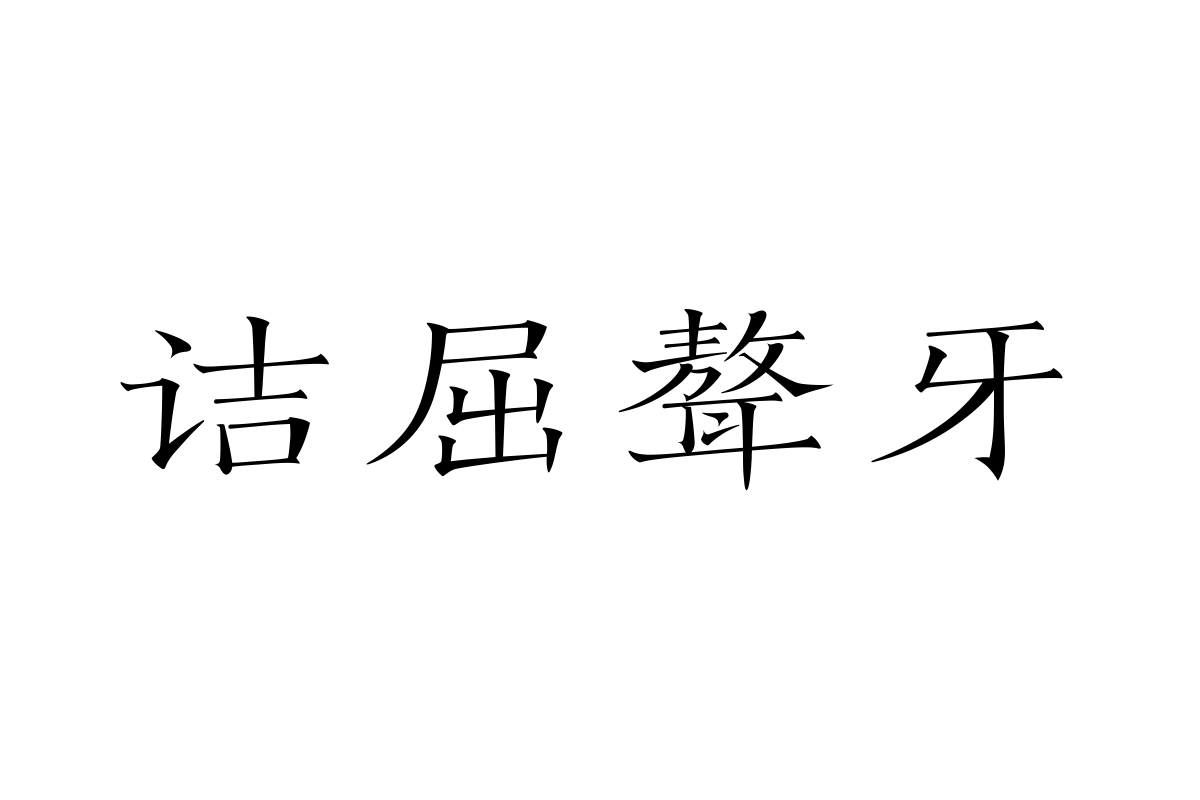
汉仪俊楷字体是一种非常受欢迎的中文字体,由汉仪公司设计。这种字体的特点是字形简洁大方,笔画流畅自然,非常适合用于各种印刷品和电子出版物。它的设计灵感来源于中国传统的楷书,但又进行了一定的创新和简化,使得字体更加易读易懂。
汉仪俊楷字体的特点包括:
1. 字形简洁:汉仪俊楷字体的字形线条清晰,没有过多的装饰性元素,使得文字看起来更加整洁。
2. 笔画流畅:字体的笔画线条流畅自然,没有生硬的感觉,使得阅读起来更加舒适。
3. 易读性强:汉仪俊楷字体的字形大小适中,间距均匀,使得文字在各种尺寸的纸张上都能清晰可见。
4. 适应性强:汉仪俊楷字体适用于各种印刷品和电子出版物,包括报纸、杂志、书籍、广告、网页等。
5. 可扩展性好:汉仪俊楷字体可以根据需要调整字号、行距、字间距等参数,满足不同场合的需求。
总的来说,汉仪俊楷字体以其简洁大方、易读性强、适应性好等特点,成为了众多设计师和出版商的首选字体。